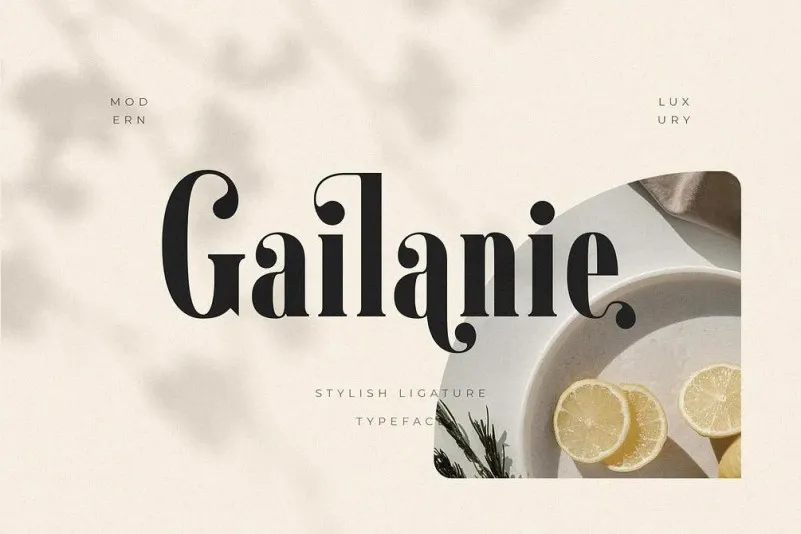
Gailanie Font – Fonte Grátis
Gailanie Font
A Gailanie Font é uma elegante fatura serif que traz seu próprio toque moderno e sofisticado para qualquer projeto editorial ou tipográfico. Cada letra foi meticulosamente cuidada por Epicatype Studio para garantir que sua textura seja única e inovadora, oferecendo um gosto refinado e contemporâneo. Esta fonte perfeita para uma variedade de aplicativos, desde marcas e logos até anúncios e embalagens de produtos, proporciona um equilíbrio elegante entre a modernidade e o estilo clássico. Com sua design moderno e detalhado, é ideal para criar designers exclusivos que se destacam na web ou em cartazes publicitários. A Gailanie Font oferece a opção de personalização perfeita para seu próximo projeto de marca ou logomarca.